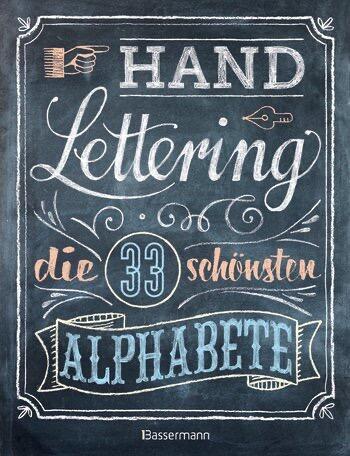
Typografie.info-Mitglied Norbert Pautner legt mit seinem Handlettering-Buch eine Beispielsammlung von Lettering-Alphabeten vor. Im Gegensatz zu anderen Büchern zum Thema (wie Lust auf Lettering oder Handbuch Handlettering) werden hier weniger die Grundlagen des Letterings vermittelt. Die diesbezügliche Einleitung nimmt nur vier Seiten in Anspruch. Den wesentlichen Inhalt des Buches bilden stattdessen die 33 Alphabetvorlagen. Pro Doppelseite wird rechts das Alphabet gezeigt und links werden Hintergründe zum Schriftstil erklärt und Tipps zur Konstruktion gegeben.
Die vorgestellten Schriftstile sind:
- Unicase-Handschrift
- Schmale Grundschrift
- Enge Schreibschrift
- Einfache Federschrift
- Weite Federschrift
- Variantenreiche Pinselschrift
- Fette Pinselschrift
- Einfache Pinselschrift
- Schildermalerschrift
- Schmale Schildermalerschrift
- Elegante Pinselschrift
- Grobe Pinsel-Blockschrift
- Borstenpinsel-Versalien
- Leichte Blockschrift
- Schmale Sans
- Geometrische Sans light
- Geometrische Sans fett
- Schablonenschrift
- Einfache Antiqua-Versalien
- Blockschrift mit Serifen
- Sport-Blockschrift
- Sport-Blockschrift Sans
- Poppige Cartoon-Schrift
- Doodle-Schrift
- Plakat-Pinselschrift
- Art-Déco Sans
- Jugendstil-Versalien
- Viktorianische Zierbuchstaben
- Schilder-Schrift mit Mini-Serifen
- Western-Schrift
- Zirkus-Schrift
- Unzialschrift
- Gebrochene Schrift